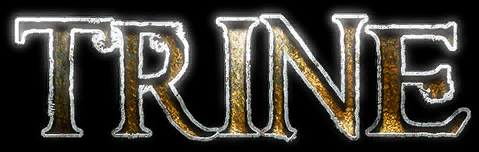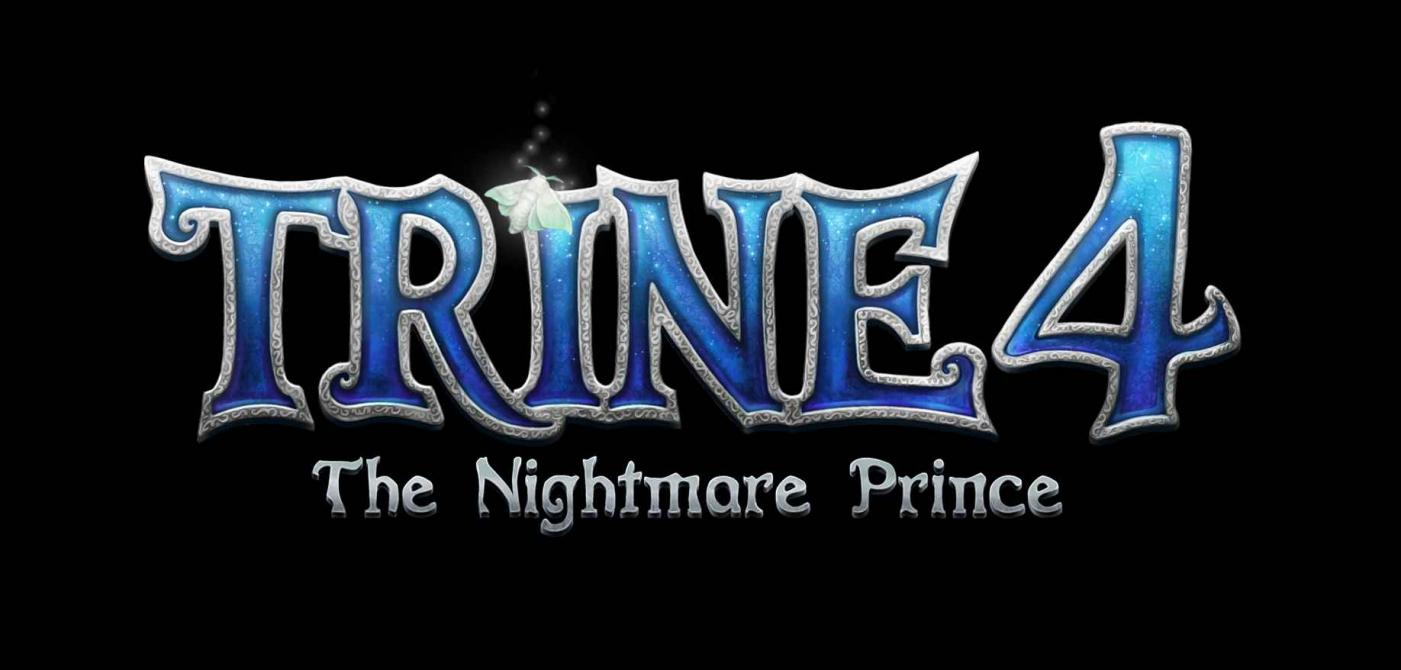
Font von Trine-Videospiel-Logo
Videospiel von 2009:
Ich habe keine anderen Schriftbeispiele gefunden...
Alternativ auch die neue Schriftart (für alle nachfolgenden Teile verwendet, hier die Kapitalen »TRINE 4«, nicht der Rest):
Was erhoffst du dir zu finden? Genau die Schrift?
Dabei ist schwer zu sagen, was die zugrundeliegende Schrift überhaupt mitgebracht haben könnte und was verbastelt ist. Outline, Struktur, Farbe ist hinzugefügt …
Ob es eine Schrift gibt, die den Rest an Macken und Unregelmäßigkeit hat :-?Wahrscheinlicher ist doch, dass die Schriftzüge komplett so gestaltet wurden. Beim ersten hat man sich vielleicht noch an irgendwelchen Antiqua-Schriften orientiert.
Naja, befürchte ich auch, aber möglicherweise wäre ja zumindest die Kontur in einer Schrift vorhanden... Auch wenn die Wahrscheinlichkeit gering ist. Aber wenn es irgendwo eine Chance gibt, dann bei den geschätzten Experten von Typografie.info! ;-)